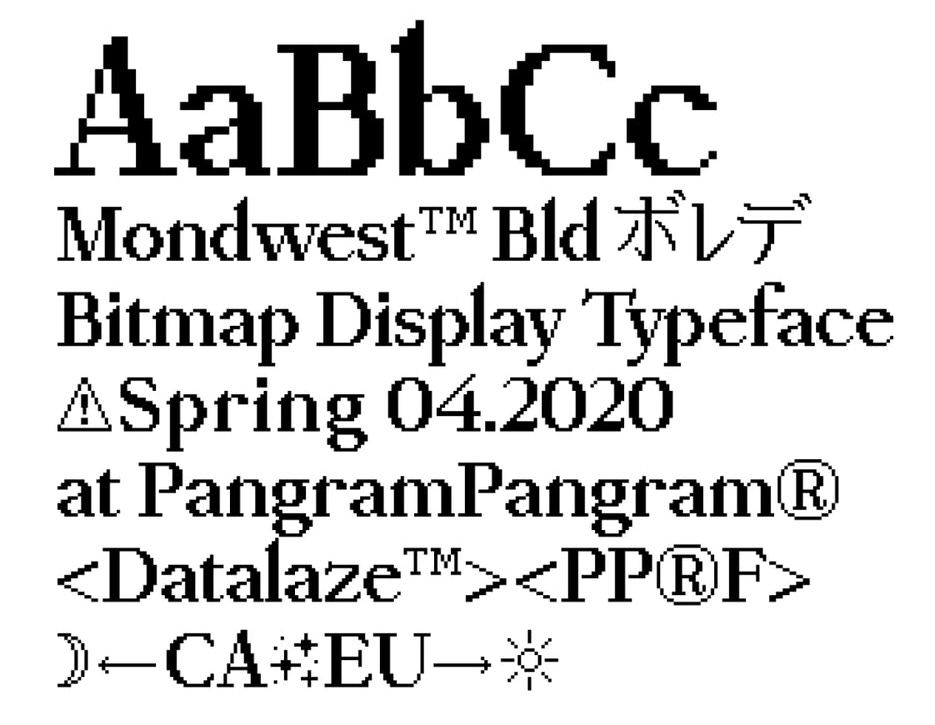
Esta lista de tipografías retro recopiladas por KorigamiK tiene un poco de todo: fuentes en tamaños muy pequeños, pensadas para programación, o para ahorrar espacio. Son ese tipo de diseños pixelados que recuerdan que un ordenador es un ordenador, con sus píxeles y cuadrículas precisas, no una hoja de papel flexible.
Las fuentes pixeladas ya parecen obras de arte perdidas en el tiempo.
– KorigamiK
- Greybeard (gratuita, licencia propia)
- Cozette (gratuita)
- PixelCode (gratuita)
- NeueBit (de pago, con prueba gratuita)
- Mondwest (de pago, con prueba gratuita)
- Departure Mono (gratuita)
- Terminus y Terminus TTF (gratuitas)
- Gohu (gratuita)
- Luculent (gratuita)
El artículo destila añoranza por lo retro, por ideas como las que transmitieron The Matrix y Mr. Robot, frente al un mundo de tipografías vectoriales completamente «sans» y planas, que parecen todas Helvética, en el que nos movemos actualmente. En fin, cuestión de gustos.